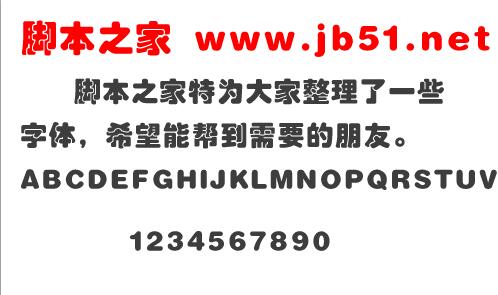
勵(lì)字琥珀簡(jiǎn)繁是一款非常不錯(cuò)的中文字體,字體傳承了個(gè)性出眾的粗體,既能給予用戶一種厚重感,又能使你擁有一種強(qiáng)烈的視覺(jué)沖擊力,可適應(yīng)于報(bào)紙和雜志和書(shū)籍中常用字體海報(bào)、個(gè)性促進(jìn)品牌標(biāo)志設(shè)計(jì)、字體設(shè)計(jì)、文本裝潢、信息展示、篆刻制模英文、數(shù)據(jù)制作、裝潢設(shè)計(jì)、視覺(jué)設(shè)計(jì)、字帖等一切合法應(yīng)用場(chǎng)景,有喜歡的朋友可免費(fèi)下載收藏。